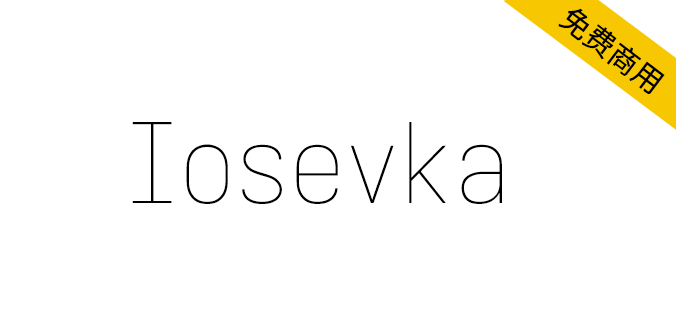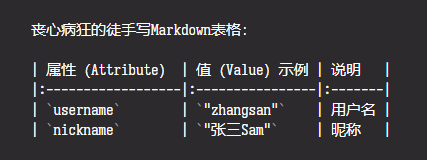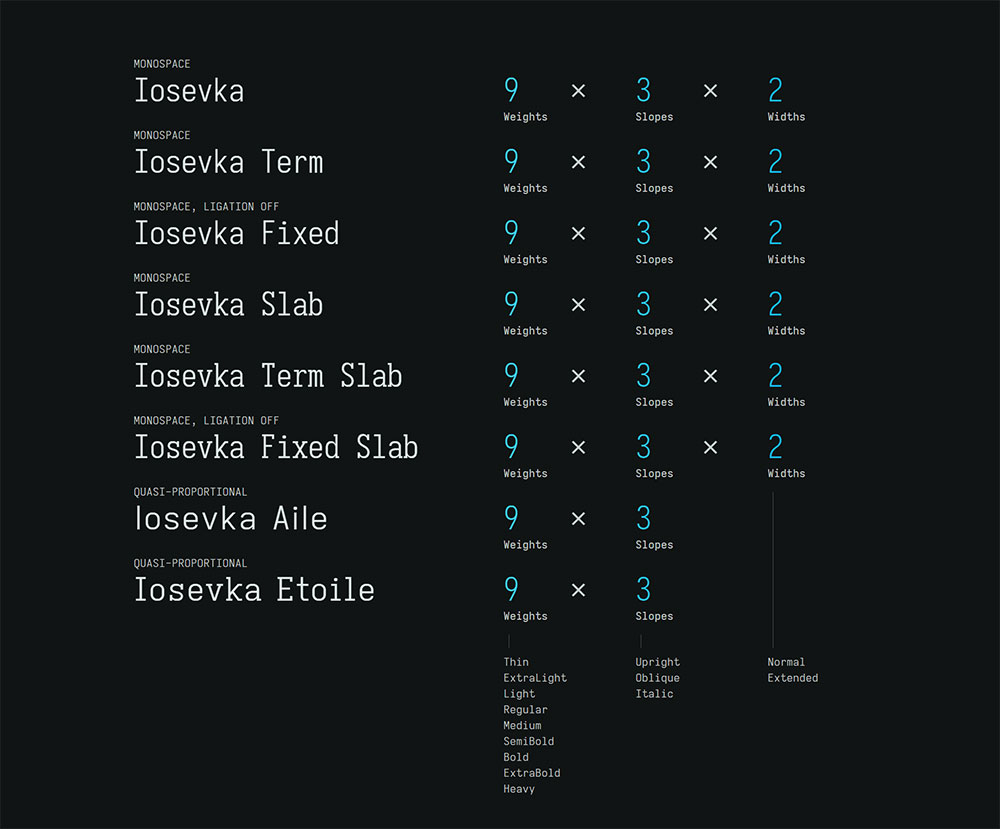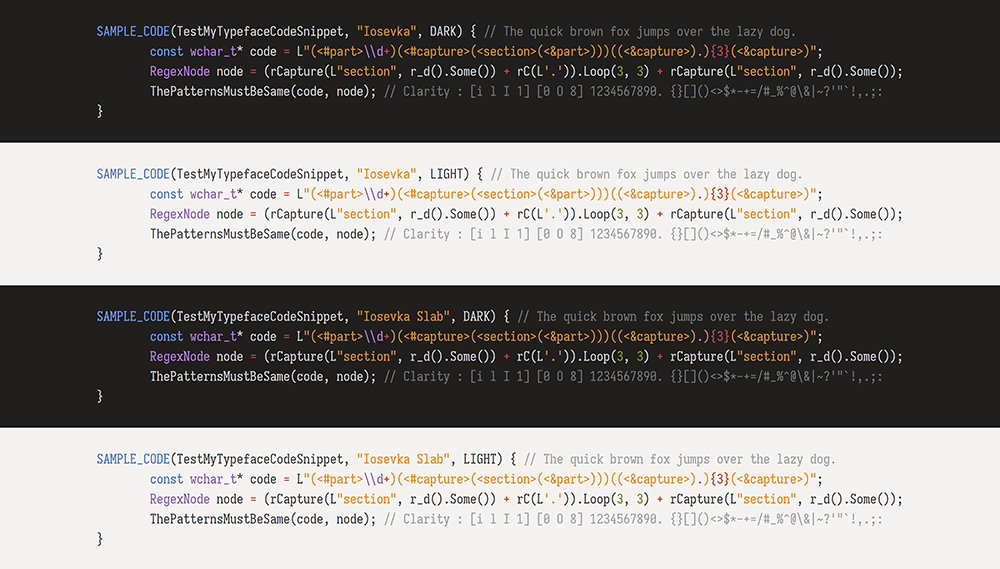
Iosevka。是一款现代化的编程字体集合,除了等宽、oO0 iIl1明显区分等基本特性外,还有很多非常现代的特性,比如:
多种风格:有非常多的字形可供选择,衬线/非衬线,多级字重,不同风格的斜体,甚至还有融合了其他常用编程字体设计风格的风味版本。(在其官网上可以动态预览各种状态的字形)
字形较窄:采用窄高的风格,水平上可以显示更多内容。(字体文件中同时包含窄和宽的字形,带有Extended的就是宽字形)
连体字形:跟JetBrains Mono一样,对很多常用的字符组合都有连体字形,美观度直线上升。
严格对齐:跟Ubuntu Mono一样,使用此字体时,中文字符宽度会严格等于2个英文字符宽度,强迫症福音。
Iosevka is an open-source, sans-serif + slab-serif, monospace + quasi‑proportional typeface family, designed for writing code, using in terminals, and preparing technical documents.